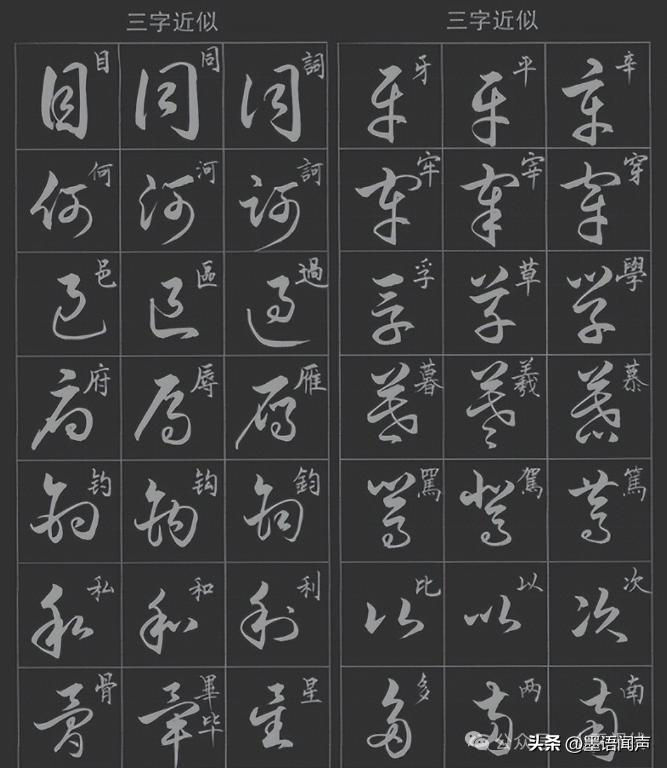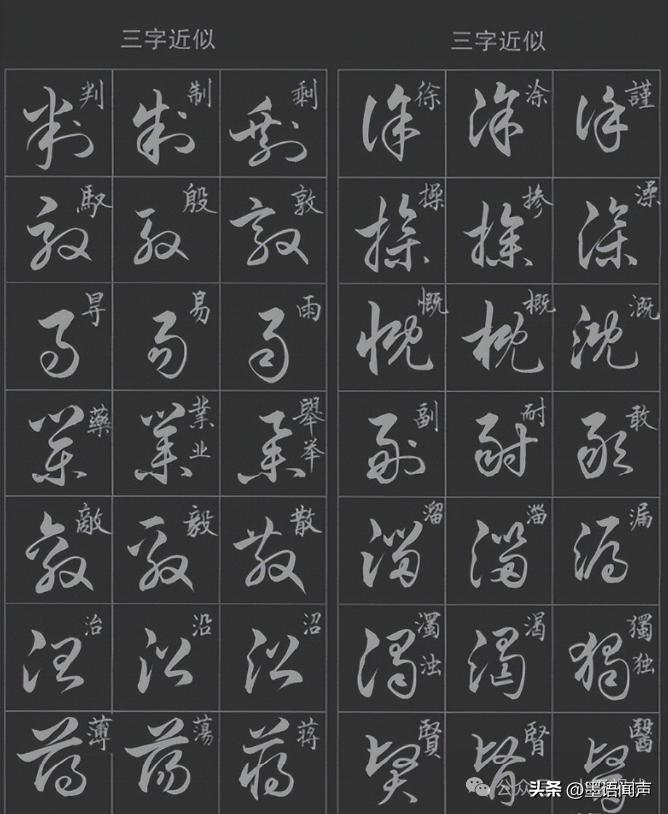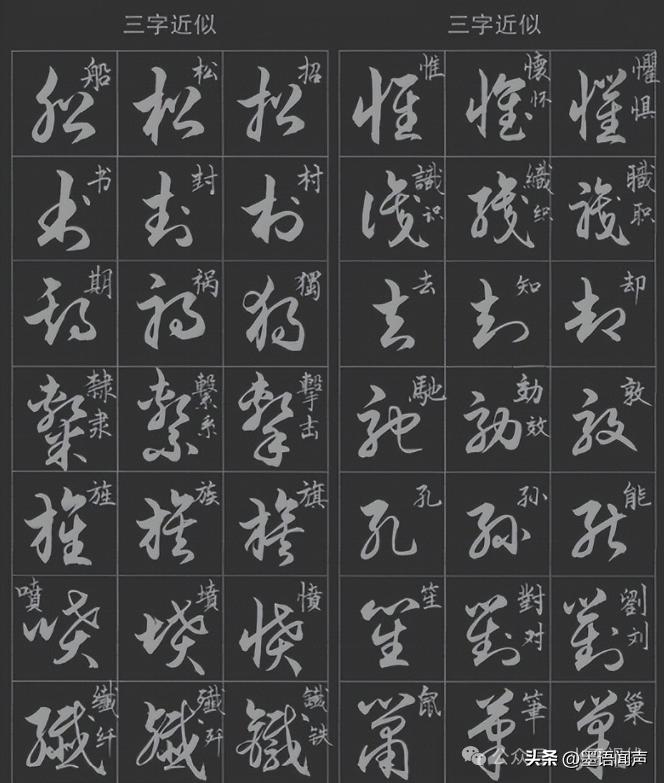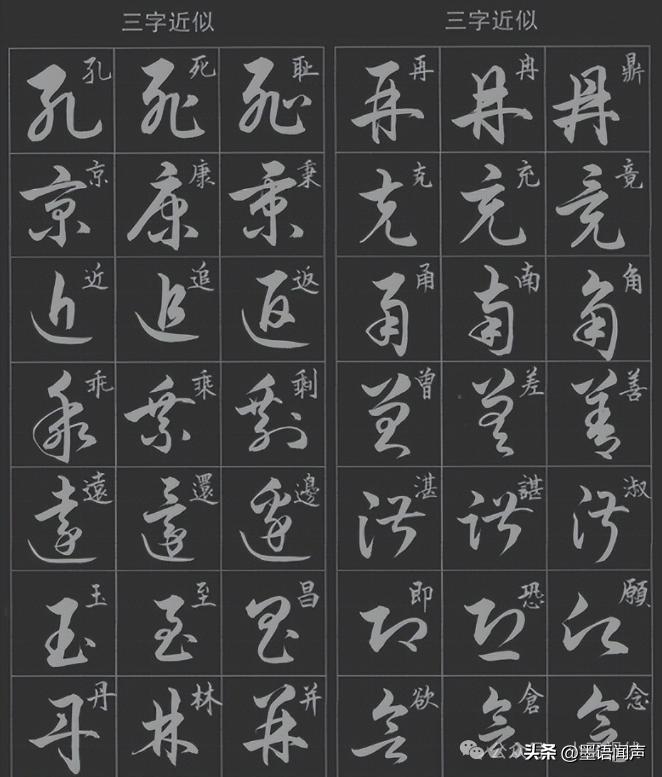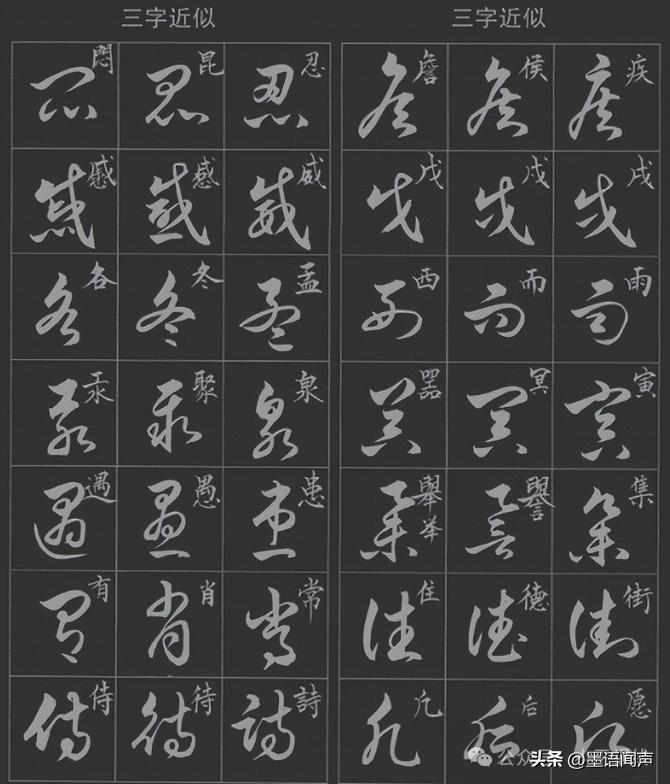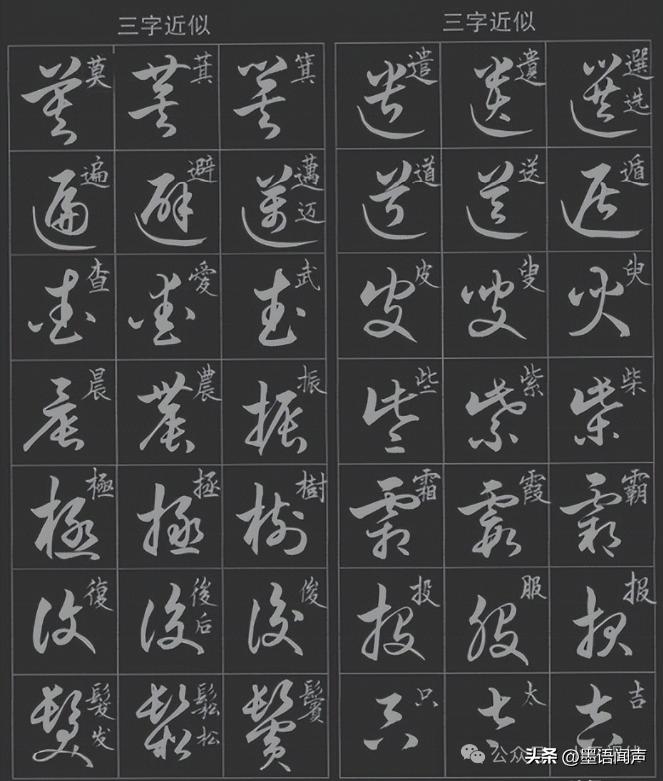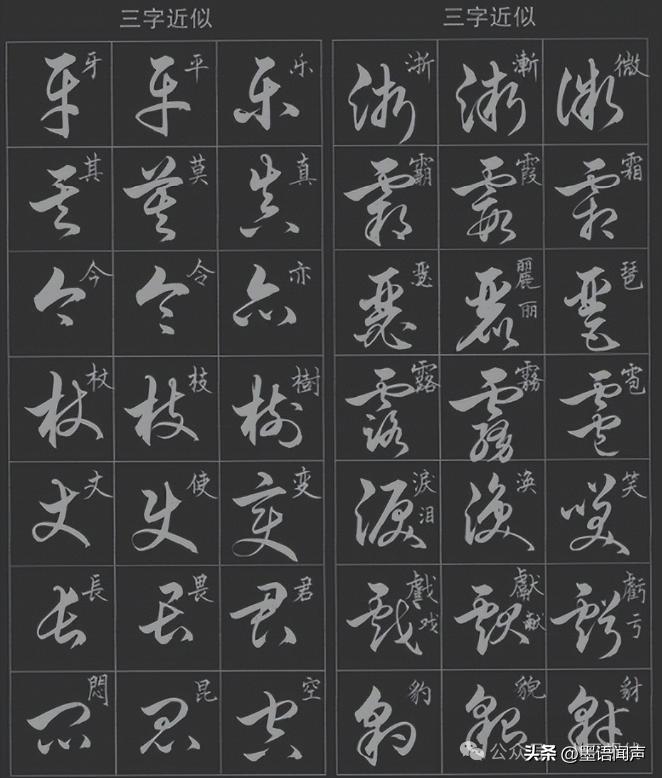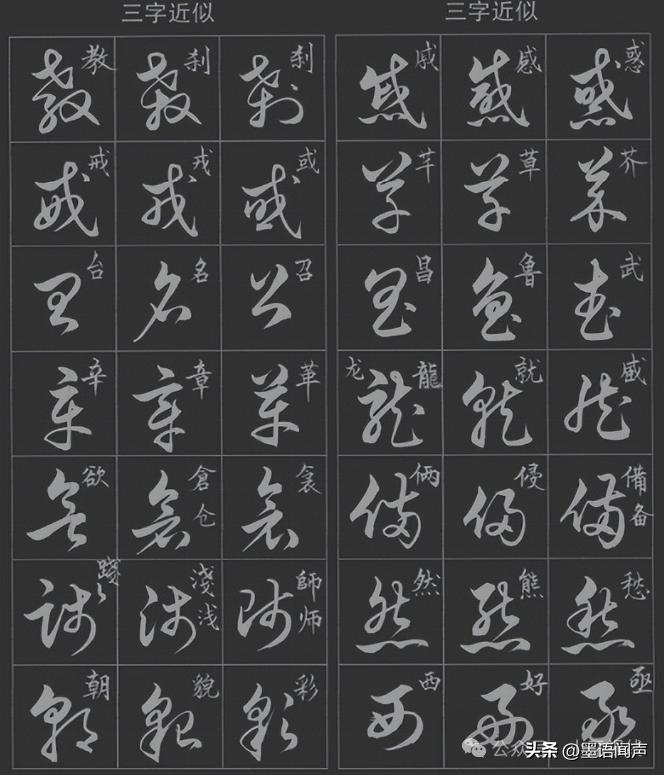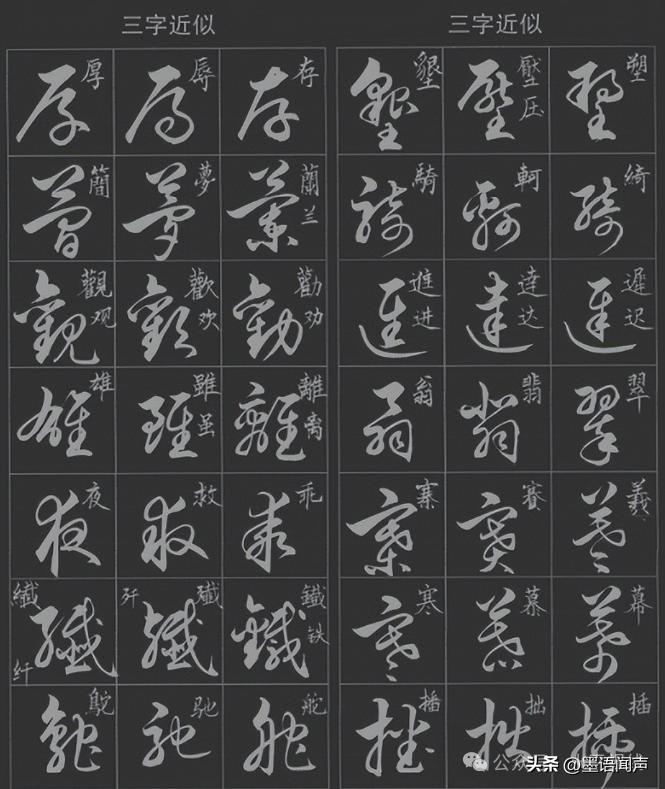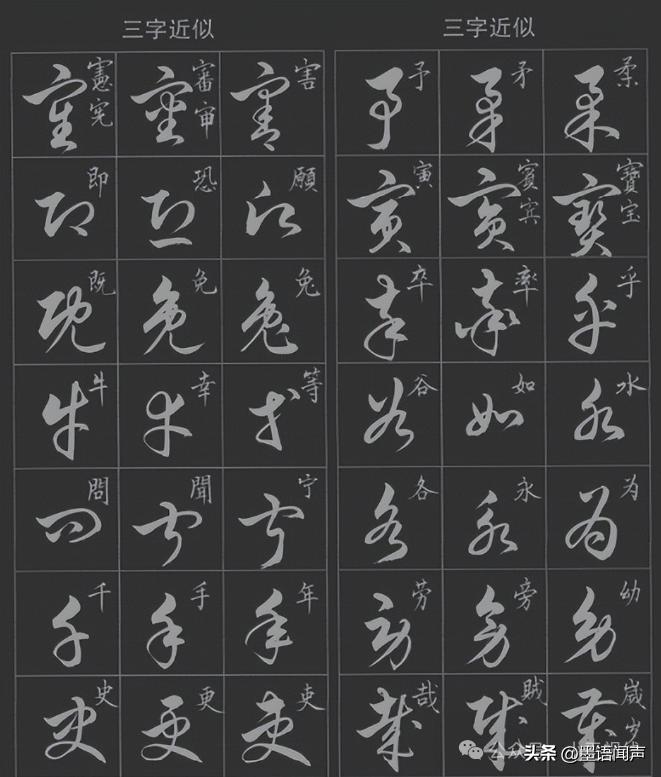
草书学习指南:从基础理论到近似字辨析的系统方法
学习草书及掌握草书近似字集,需从基础理论、临摹实践、对比辨析、系统总结四个方面入手,结合科学方法与持续练习,逐步提升对草书的认知与书写能力。
学习草书的基础准备
了解草书历史与特点
历史脉络:草书起源于汉代,分为章草(隶书草化)、今草(楷书草化)和狂草(艺术化发展)。推荐阅读《中国书法史》或观看纪录片《书法五千年》中的草书专题。
核心特点:笔画简化、连笔流畅、结构自由,但需遵循“草法”(草书书写规范),避免随意造字。
选择经典字帖
入门推荐:
孙过庭《书谱》 :理论结合实践,适合初学者理解草书笔法与结构。
王羲之《十七帖》 :今草典范,字形规范,适合临摹基础。
怀素《自叙帖》 :狂草经典,适合进阶学习线条变化与节奏。
工具准备:兼毫毛笔、生宣或半生熟宣纸、墨汁、字帖放大本(便于观察细节)。
草书临摹与笔法训练
分阶段临摹第一阶段:单字精临选择字帖中结构简单的字(如“之、也、不”),观察其起笔、行笔、收笔的连贯性。重点练习“使转”(笔画转折处的圆润过渡)和“牵丝”(笔画间的连带线条)。第二阶段:通篇临摹逐段临摹《书谱》或《十七帖》,注意字与字之间的呼应关系,体会行气(整行字的流动感)。第三阶段:背临与创作脱离字帖,凭记忆书写,再与原帖对比修正。尝试用草书书写古诗或短文,培养应用能力。
笔法专项训练
中锋用笔:保持笔尖在笔画中心运行,使线条饱满有力。
提按变化:通过提笔(笔画变细)和按笔(笔画变粗)表现节奏。
速度控制:狂草需快速书写,但需在快速中保持结构准确。
草书近似字集的辨析与记忆
草书中许多字因简化或连笔导致形态相似,易混淆。需通过对比、联想和系统归纳来掌握。
常见近似字分类
结构相似型:
“天”与“夫” :天字末笔为捺,夫字末笔为点。
“未”与“末” :未字两横长短相近,末字下横长于上横。
连笔差异型:
“言”与“计” :言字上部为“亠”加三横,计字上部为“讠”的简化连笔。
“有”与“在” :有字上部为“”,在字上部为“土”的连笔。
部首替换型:
“辶”(走之底)与“廴”(建字底) :如“过”与“建”的草书形态。
记忆方法
对比法:将近似字并列书写,标注差异点(如笔画长短、方向、连笔方式)。
联想记忆:将字形与实物或动作关联(如“飞”字像鸟展翅)。
口诀法:编简短口诀辅助记忆(如“天末捺,夫末点”)。
工具辅助:使用《草书字典》或APP(如“以观书法”)查询字形,观察动态书写演示。
常见误区避免
忽视草法规范:草书虽自由,但需遵循约定俗成的写法,不可随意简化。
过度追求速度:初学时应以结构准确为主,熟练后再提升速度。
孤立练字:需结合上下文理解字在篇章中的作用,避免单字僵硬。
通过系统学习与持续实践,您将逐步掌握草书的书写技巧,并能准确区分近似字,最终形成个人风格。草书之美在于“狂而不乱,草而有法”,愿您在书写中感受这份自由与韵律!